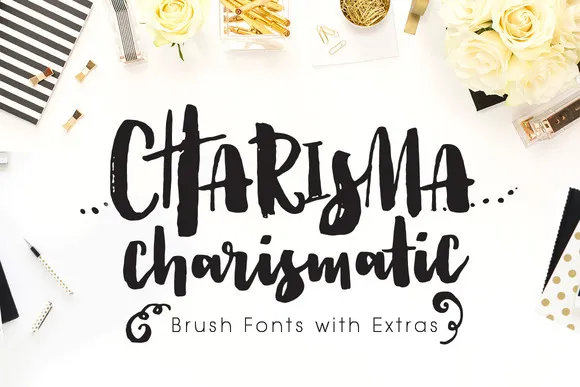
Charisma Brush Fonts with Extras – Download Grátis
Aqui está uma descrição em português para a página de download do Charisma Brush Fonts with Extras: Introduzimos Charisma, nossa nova fonte brushy moderna desenvolvida especialmente para a tendência elegante e a letra brush. Este design exibe características leves e sofisticadas que se adaptam perfeitamente à criação de mensagens impactantes e gráficos incríveis. Estamos muito entusiasmados com o Charisma Brush Fonts with Extras, um conjunto de fontes com decorações adicionalmente interessantes para complementar essa beleza moderna. Estas decorações oferecem uma ampliação do estilo brushy, adicionando um toque único e personalizado a qualquer projeto. Charisma é perfeito para designers gráficos que desejam incorporar um aspecto elegante e sofisticado em seus projetos, sejam eles identidades de marca, layouts de newsletters ou elementos de website. Como uma fonte brushy, Charisma oferece uma aparência suave e fluida, criando letras bem formadas e perfeitamente integráveis no design de sua escolha. Nosso desejoso é que o Charisma Brush Fonts with Extras seja tão amado quanto nós estamos ao desenvolvê-lo. Estamos ansiosos para ver como você usará este conjunto de fontes com extras!